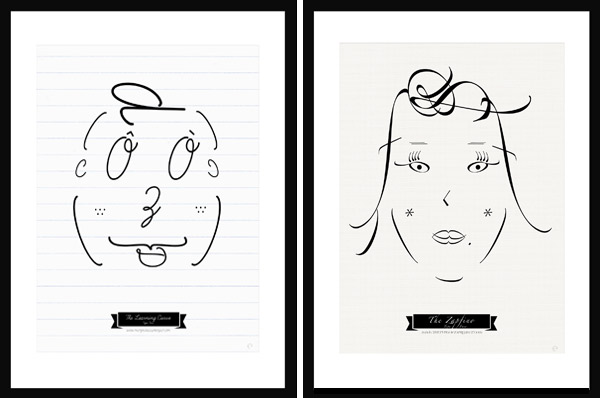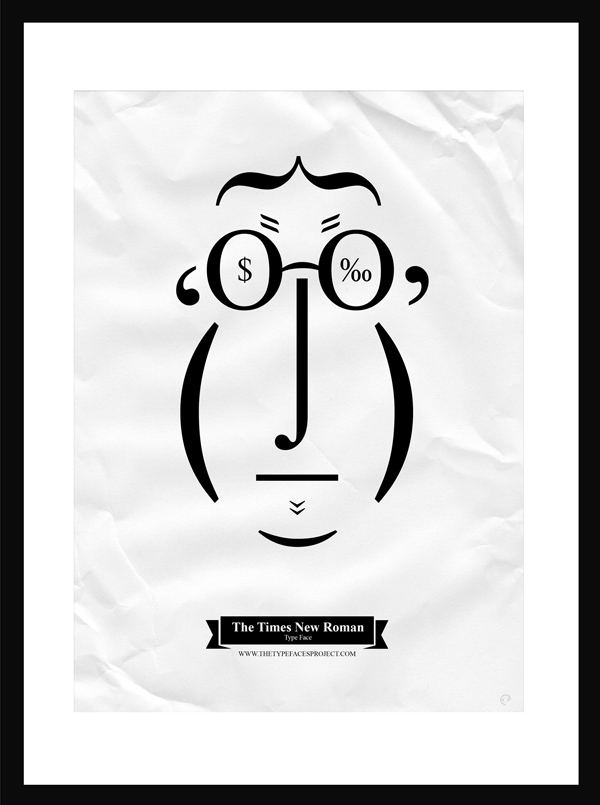
The Type Faces Proyect de Tiago Pinto pone caras a todas las fuentes
El proyecto Type Face nació como una diversión para su diseñador Tiago Pinto, quien estaba a punto de trasladarse desde Lisboa a Ámsterdam cuando surgió esta idea: al igual que las personas cada tipografía cuenta con una personalidad que puede expresarse en su propio rostro.
The Type Faces Project con tipografía The Baskerville, Tiago Pinto, 2012.
El diseñador portugués estaba jugando con el programa de diseño gráfico Illustrator cuando se le ocurrió la idea de crear caras y buscar la fisionomia de diferentes tipografías. Comenzó con la fuente que viene predeterminada por Adobe, Myriad Pro.
The Type Faces Project con tipografías Myriad Pro y Frutiger, Tiago Pinto, 2012.
Tras este primer contacto con Type Face, siguió con otros tipos de letras como Frutiger, Bodoni -que aportaba el toque italiano con el bigote- y Futura.
The Type Faces Project con tipografía Bodoni, Tiago Pinto, 2012.
The Type F aces Project con tipografía The Futura, Tiago Pinto, 2012.
The Type Faces Project con tipografía Courier New, Tiago Pinto, 2012.
The Type Faces Project con tipografía The Times New Roman, Tiago Pinto, 2012.
The Type Faces Project con tipografías Learning Curve y Zapfino, Tiago Pinto, 2012.
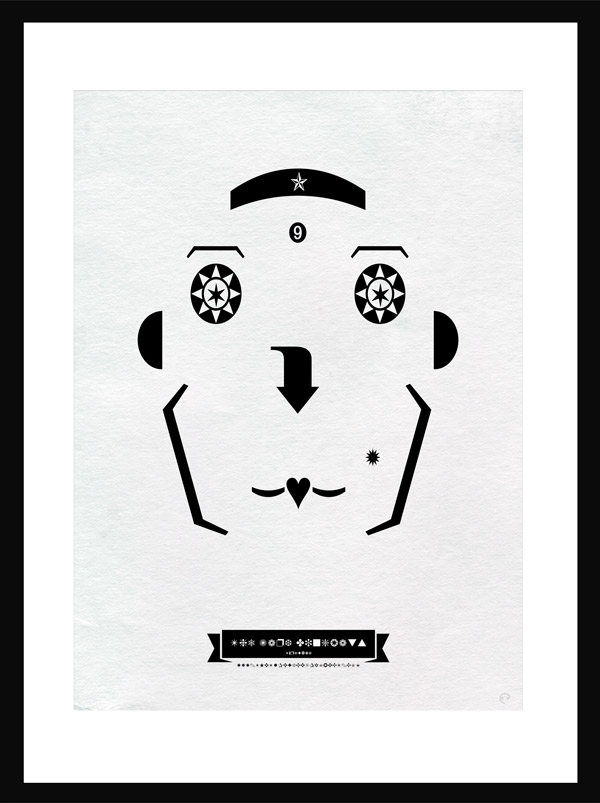
The Type Faces Project con tipografía Dingbats, Tiago Pinto, 2012.